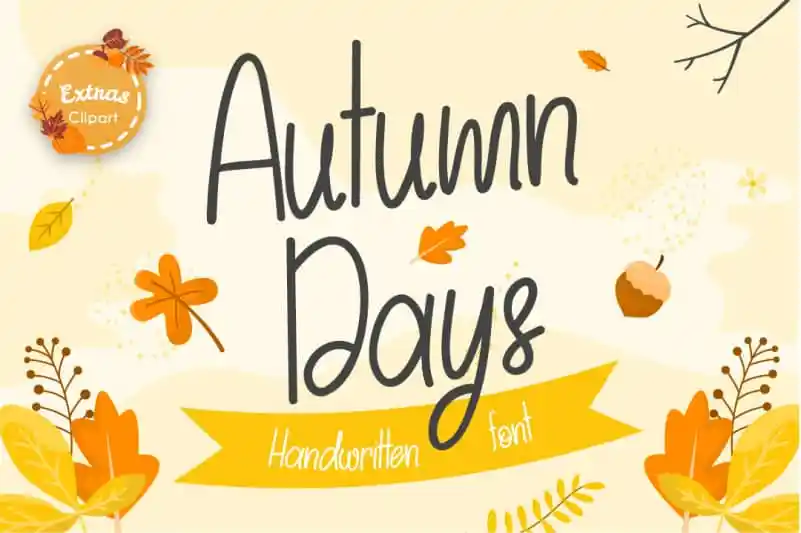
Autumn Days Handwritten Font – Download Grátis
A Autumn Days Handwritten Font é uma elegante caligrafia curvilínea que se assemelha a uma conversa sincera entre amigos. Suas linhas suaves e sua tipografia amigável tornam essa fonte perfeita para qualquer projeto, desde criativos cartões de aniversário até gráficos sofisticados para postagens de redes sociais. Esse é um recurso que pode transformar seu trabalho em algo único, elegante e definitivamente impressionante. Suas versáteis aparências a tornam uma escolha excepcional tanto no mundo das celebrações quanto na publicidade online. Experimente ela; sua paixão por essa fonte será fácil de ver em qualquer projeto que você começar.